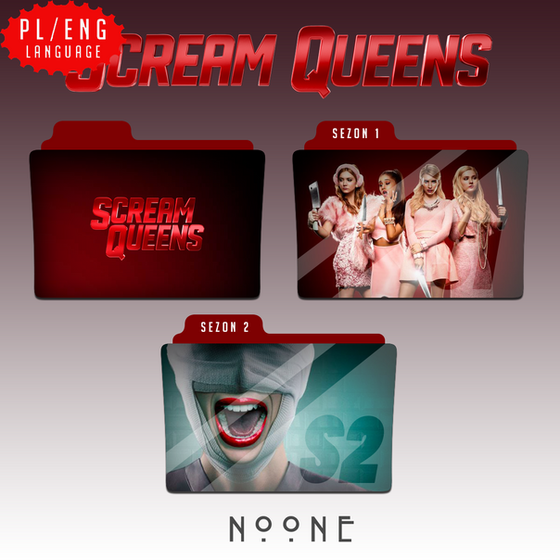
Espero que les guste este Style de photoshop hecho por mi, adicional puse la la font que se usó en el logo de Scream Queens (la fuente fue editada así que no es igual)*Ignoren el error que hay en la previa*
Creo que sí es la misma, pero la pusieron en negrita y juntaron más las letras.
Igual está muy lindo y muy parecido.